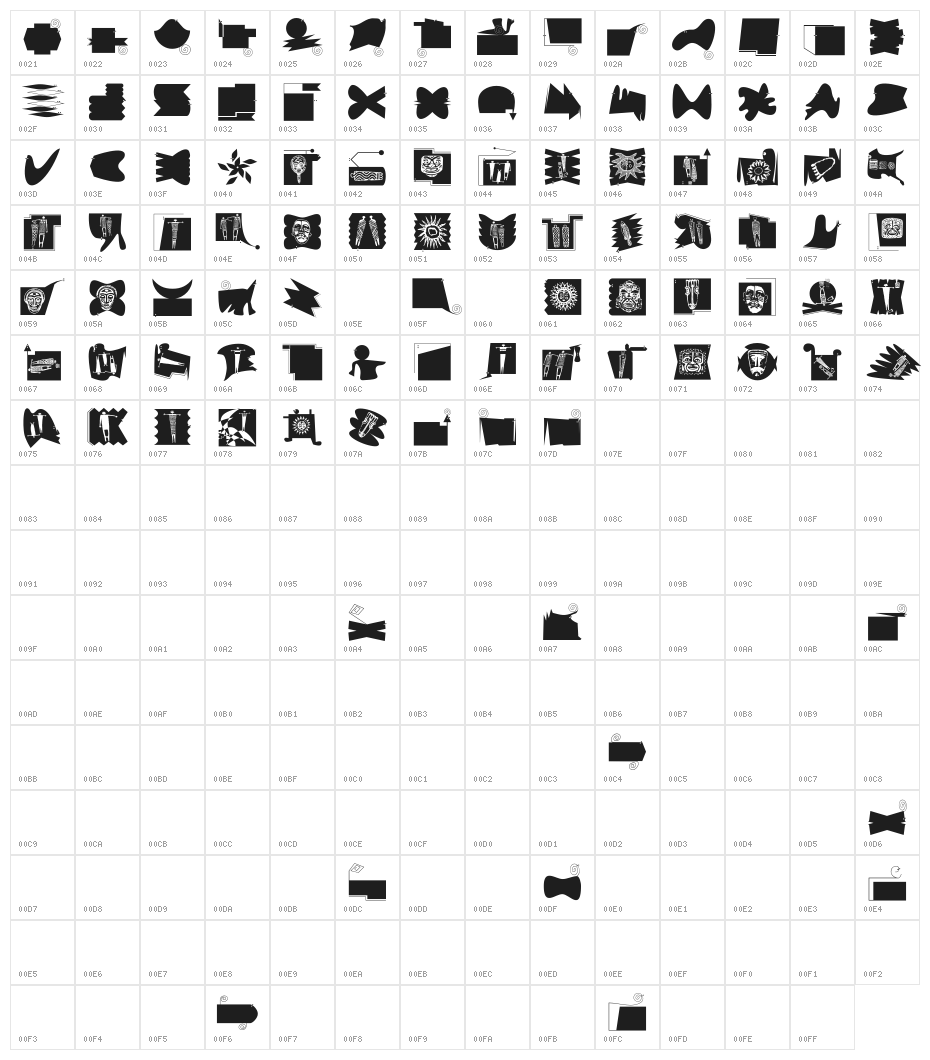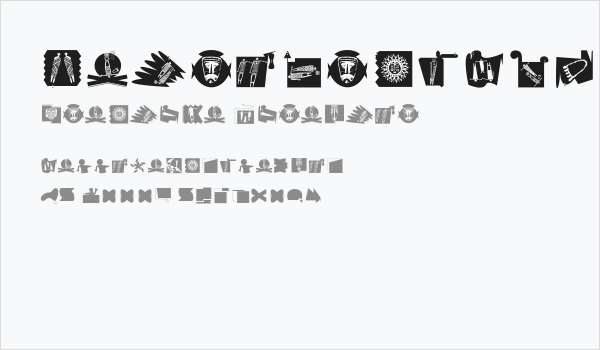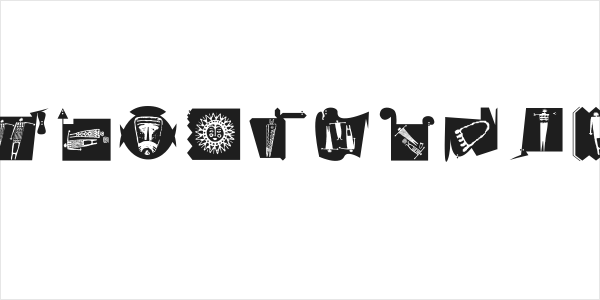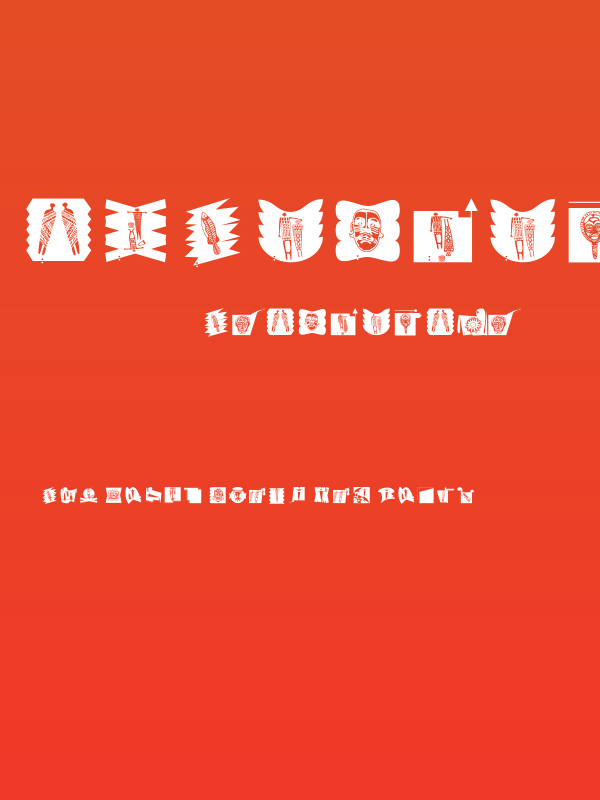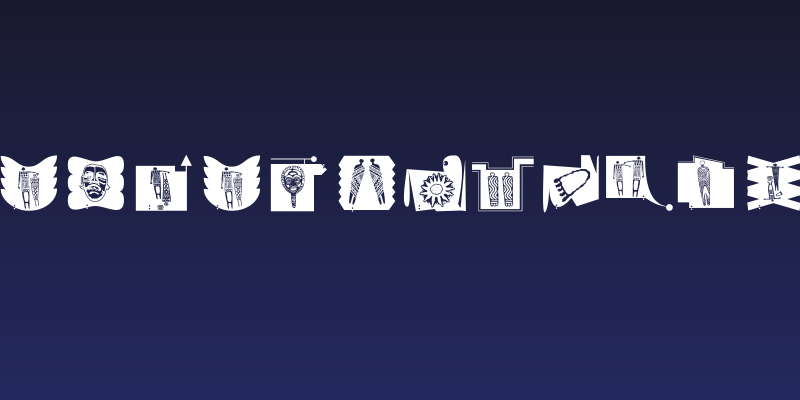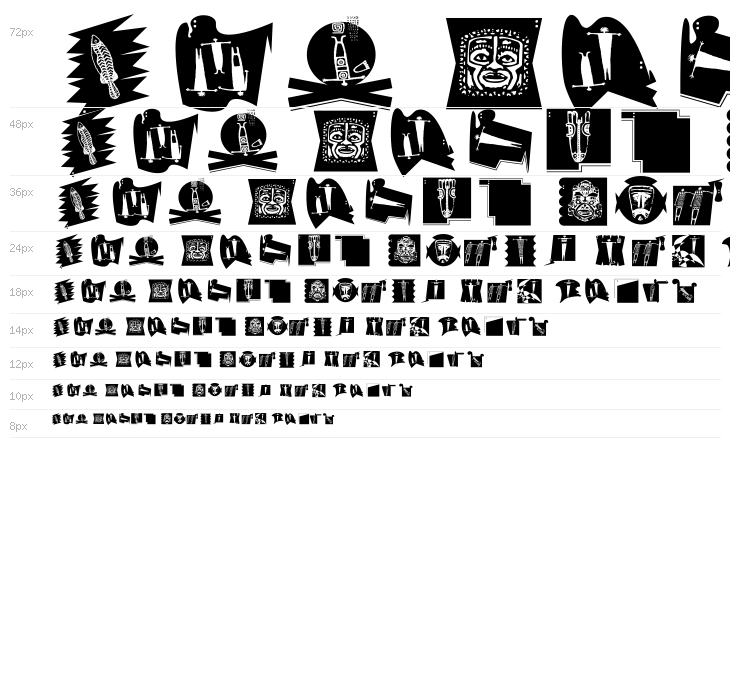
PetrographsInverse Font
| Anwendungsfall | Logos, Posters, Artistic Designs |
| Vorgeschlagene Projekte | Ideal for use in artistic projects, cultural event posters, album covers, or any design requiring a historical or tribal aesthetic. |